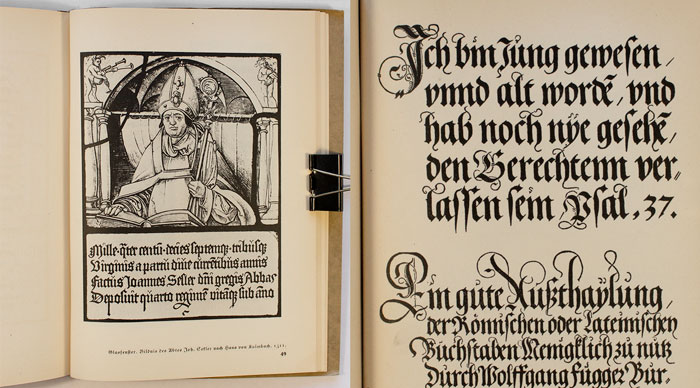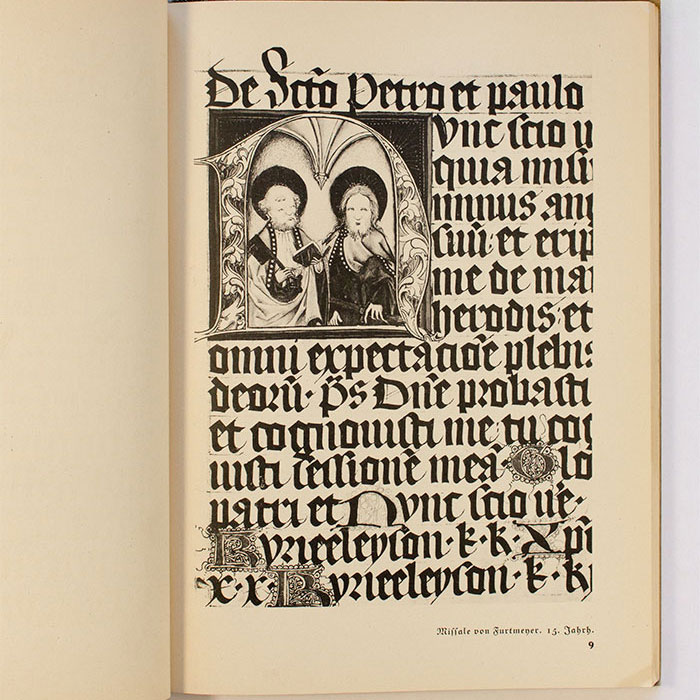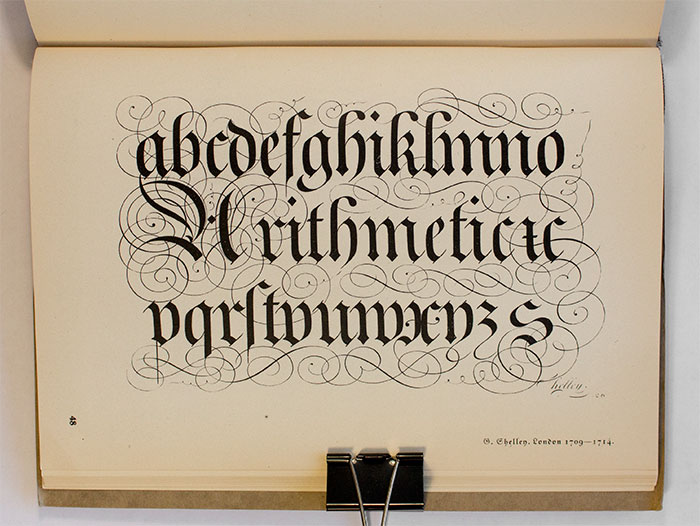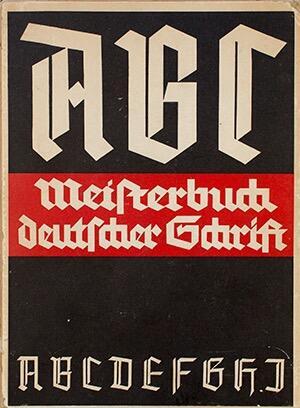
Meisterbuch deutscher Schrift
Im Meisterbuch deutscher Schrift zeigt Kurt Siebert anhand von Bildtafeln über 64 Seiten die Entwicklung der gebrochenen Schriften. Den Anfang machen Nachbildungen alter gotischer Handschriften. Anschließend folgen gebrochene Druckschriften. Es folgen Abbildungen aus Schreibmeisterbüchern, wie denen von Johann Neudörffer der Ältere. Den Abschluss bilden Abbildungen von Anwendungsbeispielen gebrochener Schrift, z.B. in Inschriften.
Das Buch erschien vermutlich Anfang der 1930er-Jahre.